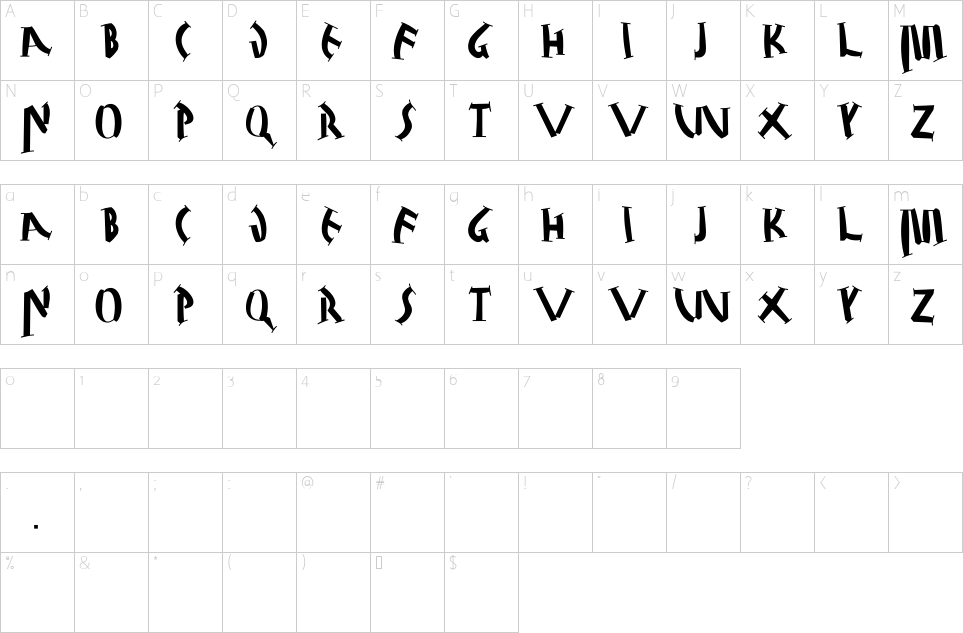
Aqui está uma descrição em português do Brasil para a página de download da fonte ‘Julius Black Font | 1001 Free Fonts’: Julius Black é uma fonte elegante e moderna, perfeita para criar um design minimalista e sofisticado. Desenvolvida pelo designer Manfred Klein 函, essa fonte oferece uma textura suave que pode tornar qualquer projeto visual mais atraente. Descubra por que muitos designers estão escolhendo Julius Black para suas obras, pois ela é a perfeita combinação de beleza e funcionalidade. Esta é uma fonte gratuita, livre de royalties, disponível para Windows e Mac. Com ela, você pode criar uma variedade de projetos, desde textos legíveis até elementos de marca, que se destacam de forma elegante e moderna. Experimente Julius Black hoje e veja como ele pode deixar seu trabalho de design mais especial.